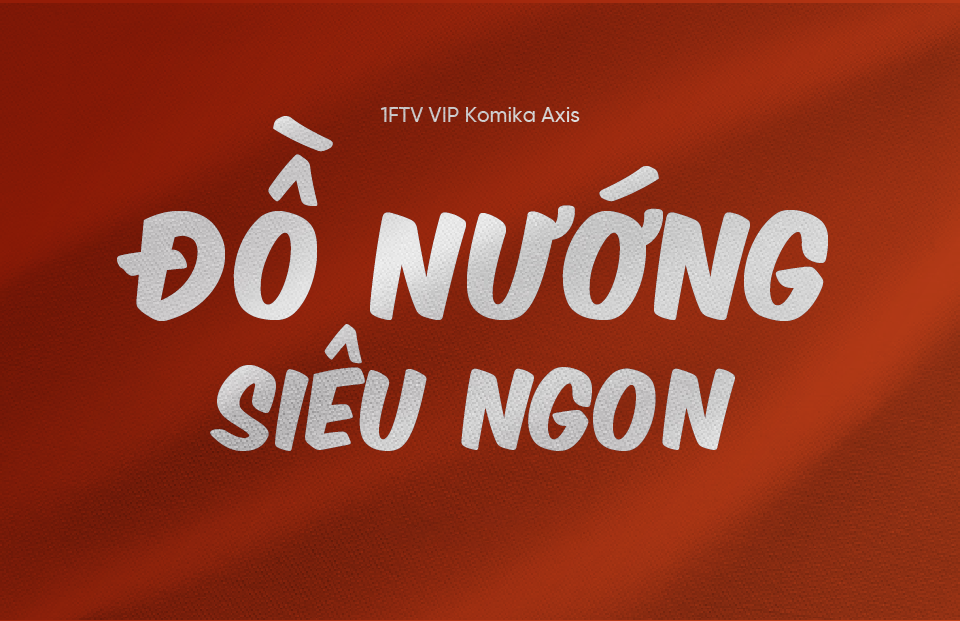
Komika title axis font là một font chữ độc đáo được thiết kế bởi WolfBainX & Apostrophic Labs vào năm 2014, nổi bật với phong cách vui nhộn và năng động.
Tác giả: WolfBainX & Apostrophic Labs
Ngày phát hành: 2014
Ngôn ngữ: Hỗ trợ nhiều ngôn ngữ, bao gồm Tiếng Việt, Tiếng Anh, và nhiều ngôn ngữ khác
Bộ Font: Komika Title
Phân loại: Cá tính, độc đáo
Kiểu chữ: Không chân
Độ dày: Semi-light (Regular)